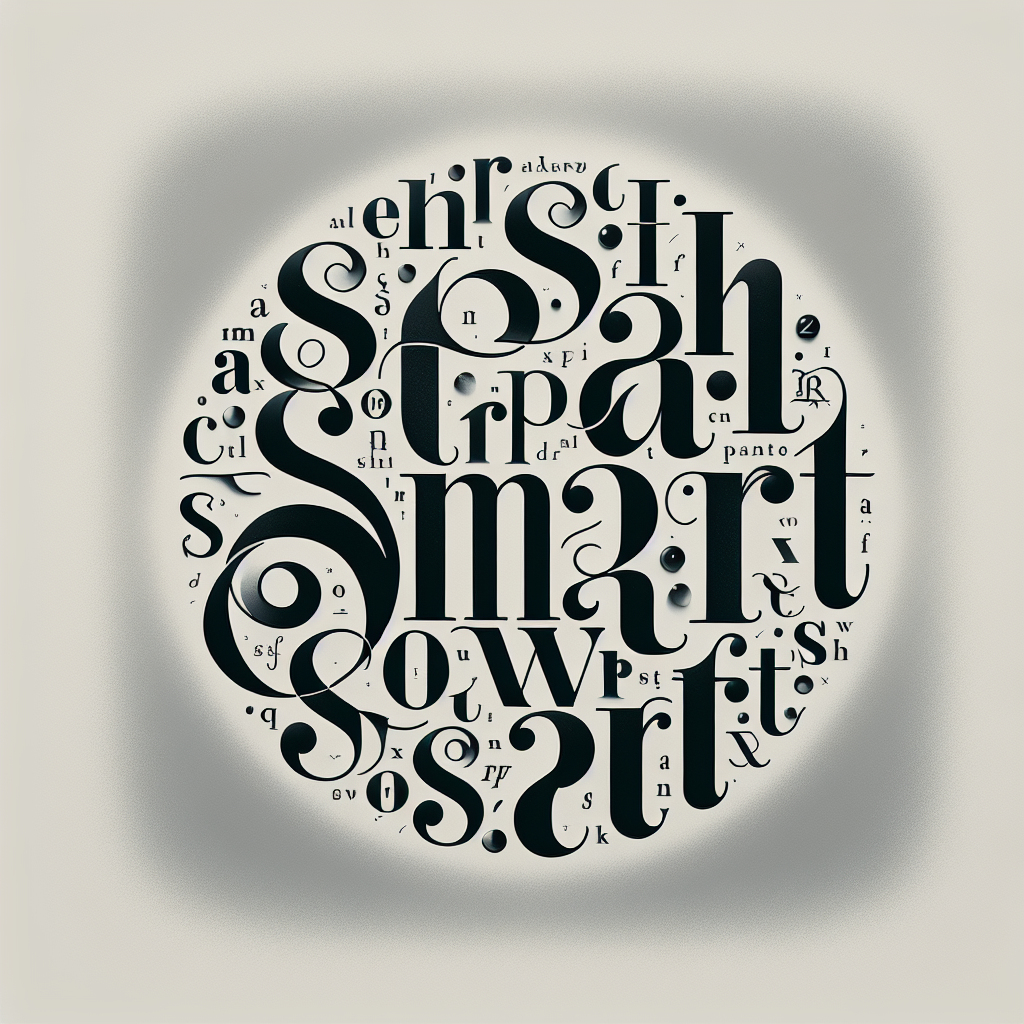
La tipografía más inteligente (y expresiva)
TypeDance es una herramienta de diseño generativo que crea logotipos tipográficos semánticos equilibrando la legibilidad de la tipografía y la fuerza expresiva de la imagen. Aprovecha un modelo CLIP preentrenado para evaluar cada diseño en un espectro tipo imagen y utiliza retroalimentación implícita y explícita de los usuarios para mejorar resultados con el tiempo. A través de controles deslizantes, indicaciones textuales y edición vectorial de alto detalle, los usuarios pueden refinar de forma iterativa desde la estética general hasta elementos individuales, logrando control preciso y resultados de alta calidad.